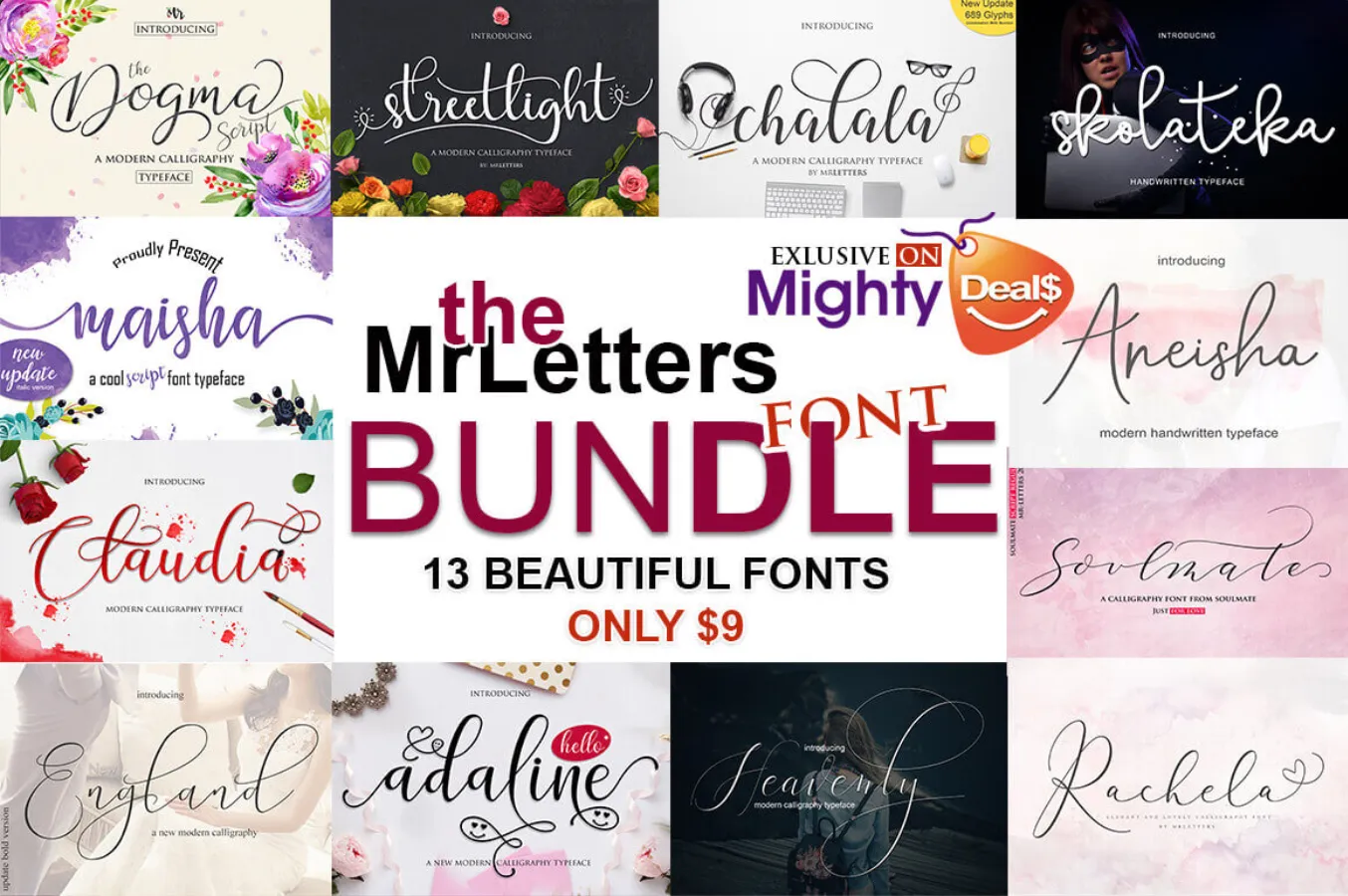
Набор из 13 современных шрифтов The MrLetters Font Bundle
MrLetters Font Bundle — это профессиональный набор, включающий 13 современных рукописных шрифтов (script typefaces). Данный пакет предназначен для дизайнеров, оформителей и всех, кто занимается созданием визуального контента, требующего эстетичных и стильных шрифтовых решений.
Продукт включает в себя 13 уникальных гарнитур, разработанных в современном стиле. Ключевые технические особенности шрифтов:
- Полная поддержка функций OpenType.
- Наличие стилистических альтернатив (stylistic alternates) для изменения начертания символов.
- Контекстные альтернативы (contextual alternates) для автоматической адаптации формы букв в зависимости от окружения.
- Дополнительные декоративные элементы в виде росчерков (swashes), позволяющие создавать уникальные композиции.
- Высокая универсальность, подходящая для профессиональной верстки и графического дизайна.
- Оформление приглашений и конвертов.
- Создание открыток, плакатов и рекламных вывесок.
- Дизайн принтов для текстильной продукции: футболок, сумок, подушек.
- Брендирование сувенирной продукции, такой как кружки и другие аксессуары.
Продукт предоставляет широкие возможности для кастомизации текстовых элементов, позволяя создавать выразительные и запоминающиеся макеты для личных и коммерческих целей.